Inilah Jenis Font yang Digunakan Google di Logo Baru Mereka
googleKamu sudah tahu kan kalau Google ganti logo? Perubahan logo baru Google memang sempat heboh beberapa hari ini. Nggak heran, sih. Sebab logo Google memang sudah sangat terkenal dan melekat pada diri banyak orang. Terutama yang setiap hari melakukan aktifitas browsing di internet.
Banyak orang juga penasaran dengan jenis font alias huruf apa yang digunakan untuk logo baru Google. Sebagian besar berpendapat font yang digunakan adalah Futura, Century Gothic, atau Relish Pro. Tapi ternyata semuanya salah, loh! Inilah jenis font yang digunakan Google di logo baru.
Kalau melihat sekilas, memang font yang digunakan tampak mirip dengan Futura atau Relish Pro, tapi ternyata bukan. Google sudah membuat font sendiri yang bernama Google Product Sans. Jenis font ini nantinya akan digunakan dalam desain berbagai produk Google yang ada.
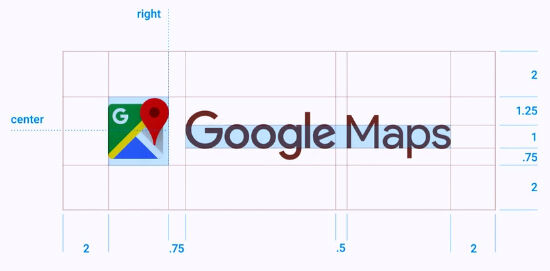
Pembuatan font ini tidak hanya memperhatikan aspek desain. Tetapi juga aspek efisiensi penggunaan bandwith. Logo Google yang lama memiliki ukuran sekitar 14.000 byte. Sedangkan logo baru ini hanya berukuran 305 byte. Sehingga halaman search Google dapat lebih ringan dibuka bahkan oleh perangkat yang koneksi internetnya super lemot.